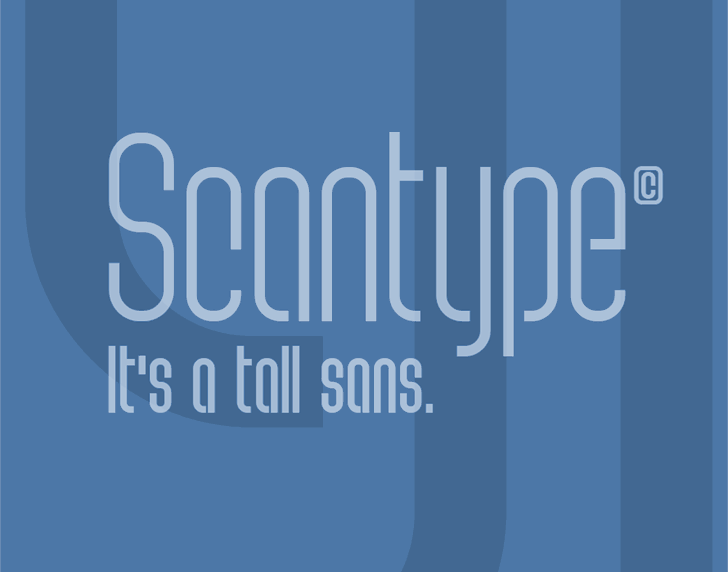
A Scantype Font é uma elegante seleção de linhas de tipo sans serif criada pelo designer Måns Grebäck. Embora seja uma fonte de tipo sem serif, a Scantype captura com precisão as nuances de texto que demandam o uso de linhas mais suaves e limpas. Ideal para ambientes modernos ou projetos que exigem leitura rápida e clara, sua simplicidade permite quebrar silhuetas convencionais em favor de uma estética minimalista e contemporânea. Adaptada para uma variedade de aplicativos digitais e impressos, a Scantype oferece um equilíbrio perfeito entre graça e funcionalidade. Para quem busca uma fonte moderna sem perder a simplicidade do tipo sans serif, a Scantype é uma escolha brilhante. Visite o site da MansGreback.com para adquirir sua licença comercial de uso.